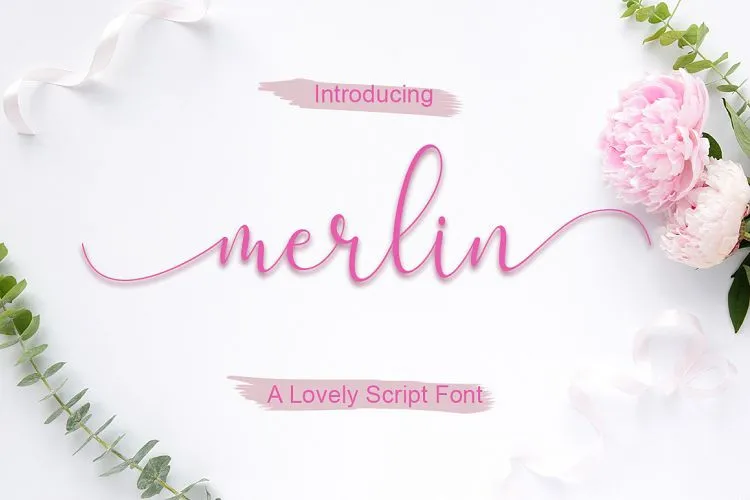
A fonte Merlin Script é uma mistura única entre clássica e moderna que captura a essência do estilo script com graça humana e personalidade. Ela retrata o aspecto perfeccionista de um texto manuscrito, onde cada caractere desafia padrões e torna-se único, como se fosse uma dança escrita. Merlin Script é fluida, limpa e simples, criando uma imagem que combina elegância com autenticidade. Perfeita para eventos formais, carteirinhas de convidados, números de mesa em salas de jantar, cabeçalhos de menus de shows ou blogs, logotipos, slider, endereços personalizados e até mesmo selos e embalagens. Esta font oferece um ar elegante sem perder a essência descontraída do estilo script. É uma escolha ideal para quem busca algo que seja tanto original quanto sofisticado.